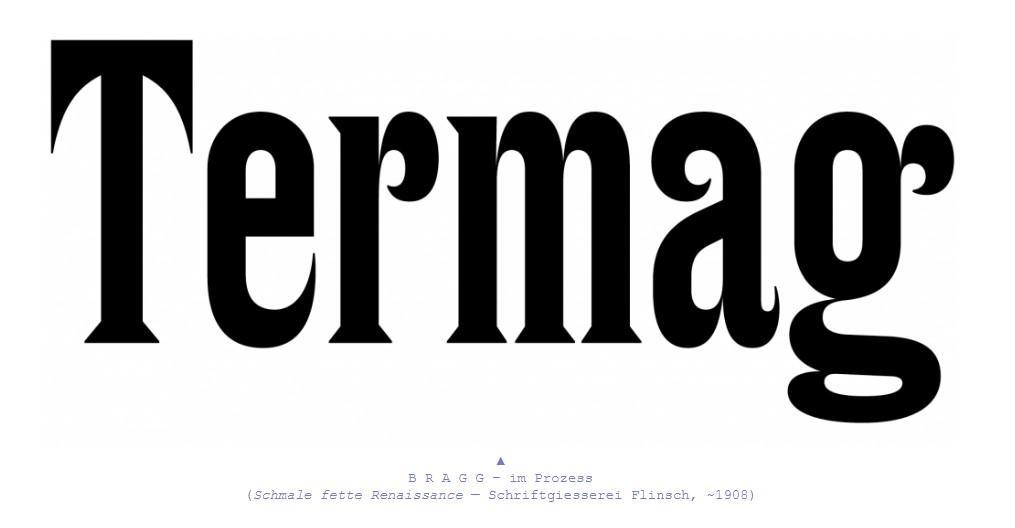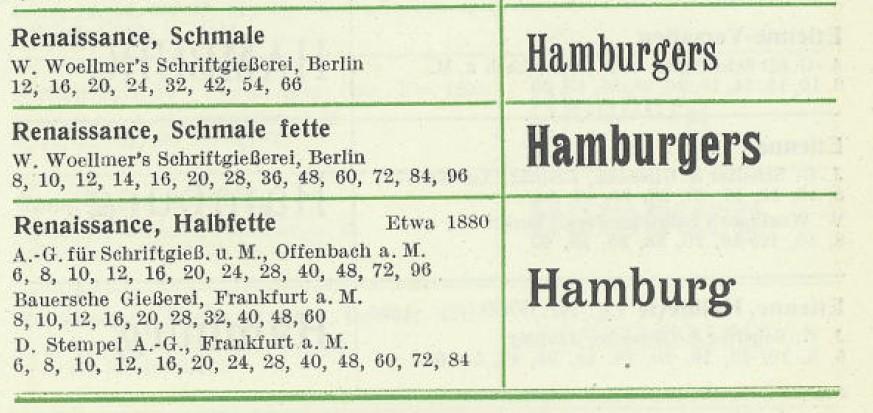
[Mitglied tobi…] Geschrieben Dezember 20, 2021 Teilen Geschrieben Dezember 20, 2021 Hallo, ich bin auf der Suche nach Textproben der Renaissance schmalfett von Wilhelm Woellmer und/oder Flinsch Anbei ein paar Muster die ich gefunden habe. Würde mich freuen wenn jemand weiterhelfen kann. Besten Dank voab, Tobias 1 Link zu diesem Kommentar
[Mitglied Bern…] Geschrieben Dezember 20, 2021 Teilen Geschrieben Dezember 20, 2021 Kann bei der Suche leider nicht weiterhelfen, aber: Der Unterscheid zwischen den Schnitten ist ja enorm. Dieses g allein... 1 Link zu diesem Kommentar
[Mitglied Thom…] Geschrieben Dezember 20, 2021 Teilen Geschrieben Dezember 20, 2021 Das Bild ist dem Scan der Hauptprobe der Schriftgießerei Schelter & Giesecke 1912 entnommen, der hier zur Verfügung gestellt wird. Darin sind aber nur die schmale Renaissance, die breite halbfette Renaissance und die breite magere Renaissance wiedergegeben. 2 Link zu diesem Kommentar
[Mitglied Dan…] Geschrieben Dezember 20, 2021 Teilen Geschrieben Dezember 20, 2021 Einige Schriftproben von Berliner Schriftgießereien kommen im Rahmen eines größeren Digitalisierungsprojekts langsam Online. Eine Seite in einer Novitäten-Katalog von Woellmer mit der schmalen fetten Renaissance kannst du hier finden bzw. herunterladen. Die kommt auf einer Seite in einer digitalisierten Handprobe ebenfalls vor. Ich gehe davon aus, dass in den nächsten Wochen einiges mehr von Woellmer bereitgestellt werden wird. In wie viele Exponate die Schrift sein wird, kann ich jedoch nicht sagen. 5 Link zu diesem Kommentar
[Mitglied Micr…] Geschrieben Dezember 20, 2021 Teilen Geschrieben Dezember 20, 2021 Ich schau gerne mal in den Woellmer-Proben die ich habe ... wird aber sicher erst im neuen Jahr etwas. 1 Link zu diesem Kommentar
[Mitglied tobi…] Geschrieben Dezember 21, 2021 Themen-Ersteller Teilen Geschrieben Dezember 21, 2021 vor 18 Stunden schrieb Dan Reynolds: Einige Schriftproben von Berliner Schriftgießereien kommen im Rahmen eines größeren Digitalisierungsprojekts langsam Online. Eine Seite in einer Novitäten-Katalog von Woellmer mit der schmalen fetten Renaissance kannst du hier finden bzw. herunterladen. Die kommt auf einer Seite in einer digitalisierten Handprobe ebenfalls vor. Ich gehe davon aus, dass in den nächsten Wochen einiges mehr von Woellmer bereitgestellt werden wird. In wie viele Exponate die Schrift sein wird, kann ich jedoch nicht sagen. Danke Dan, kannst du mir sagen, wie ich in den digitalisierten Sammlungen eventuell andere Schriftmusterbücher suchen kann? Wenn ich nach Woellmer suche erscheint nichts. Link zu diesem Kommentar